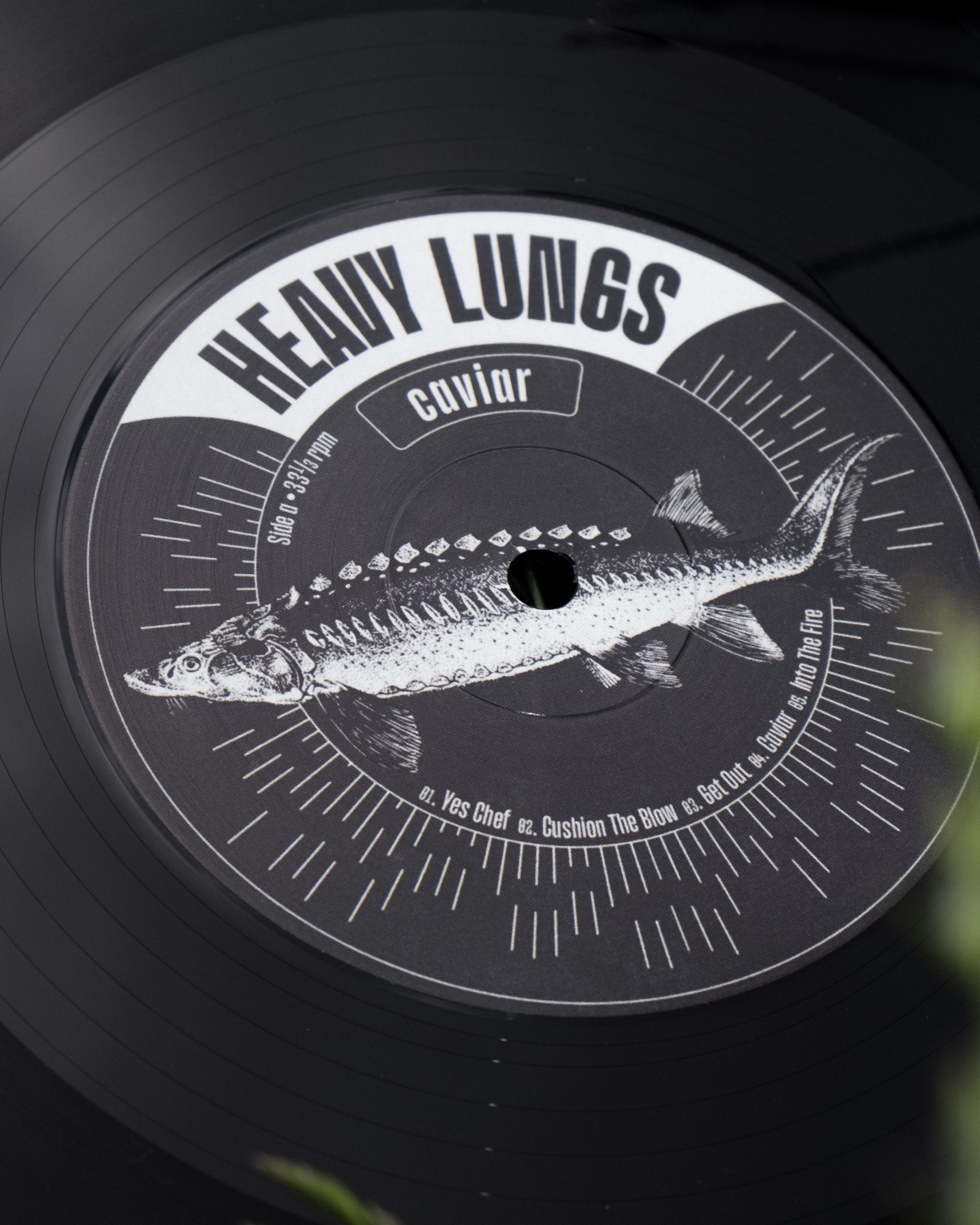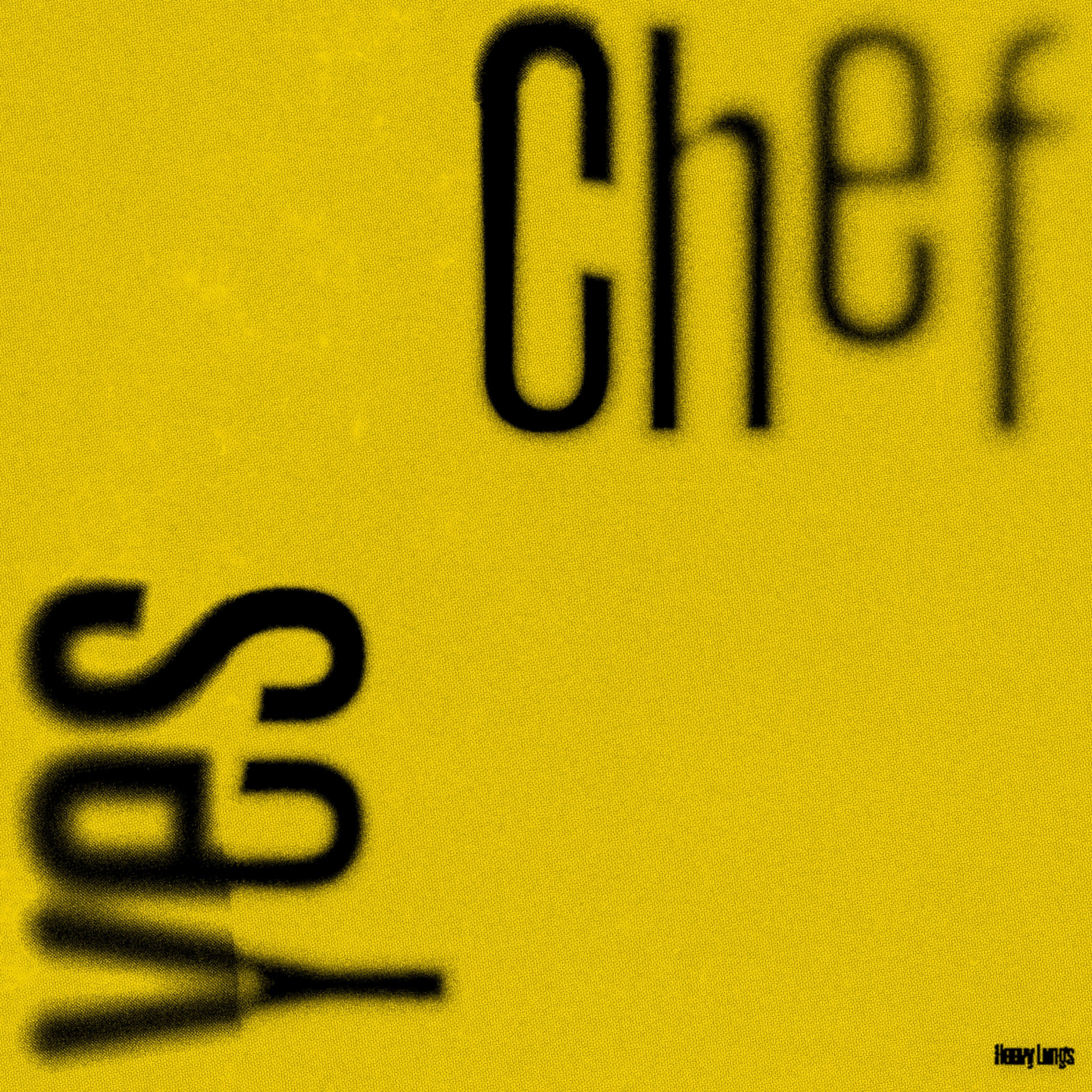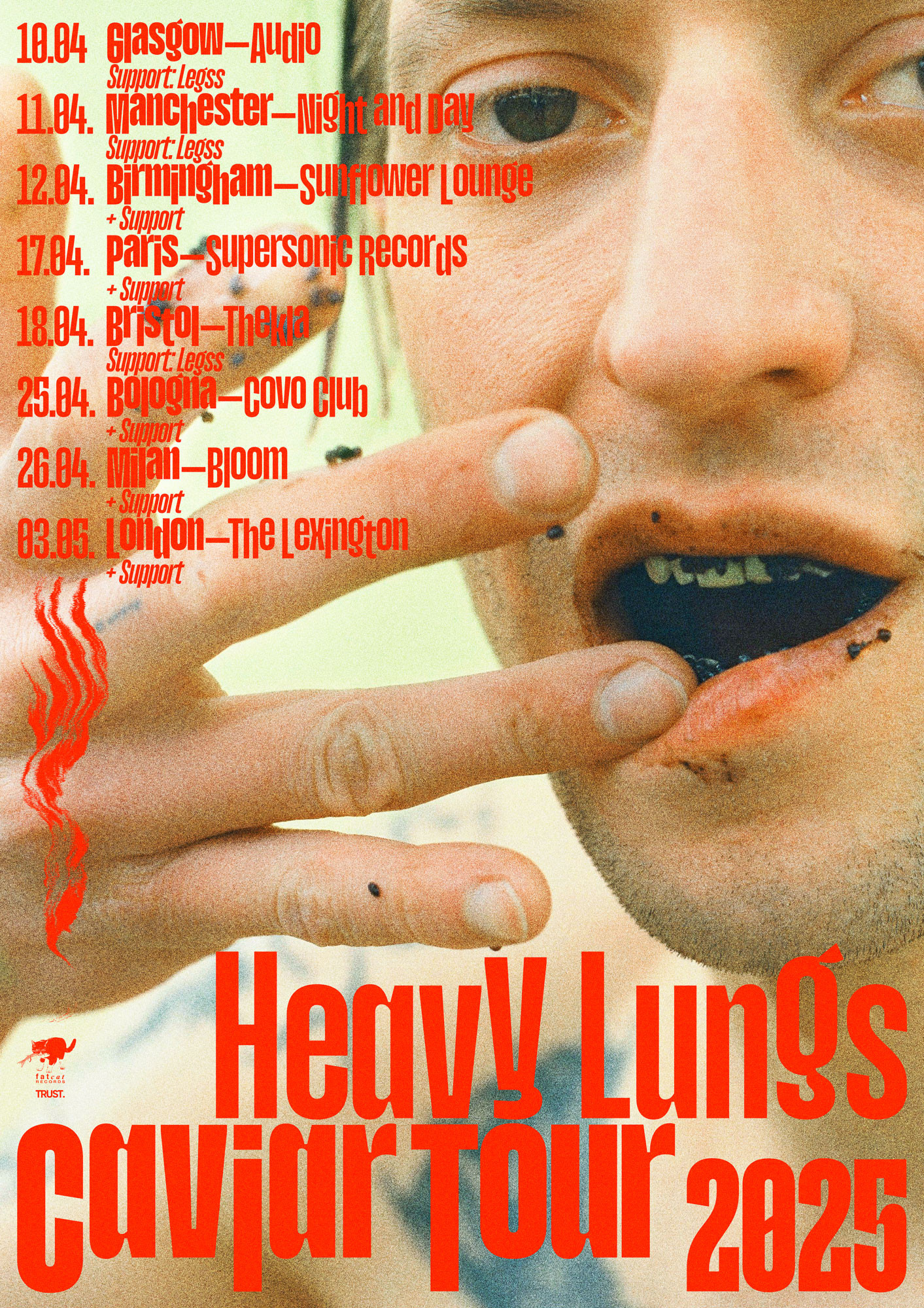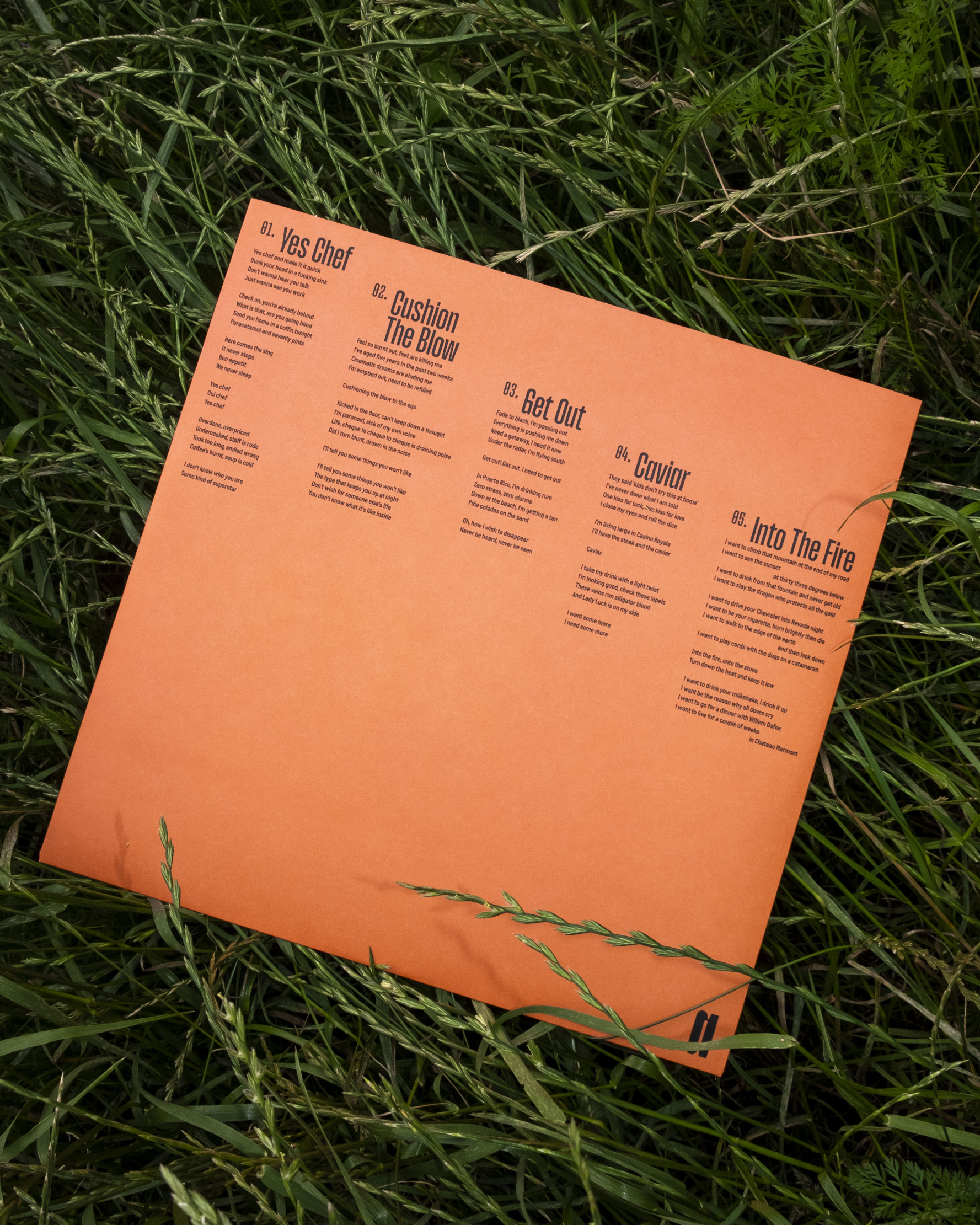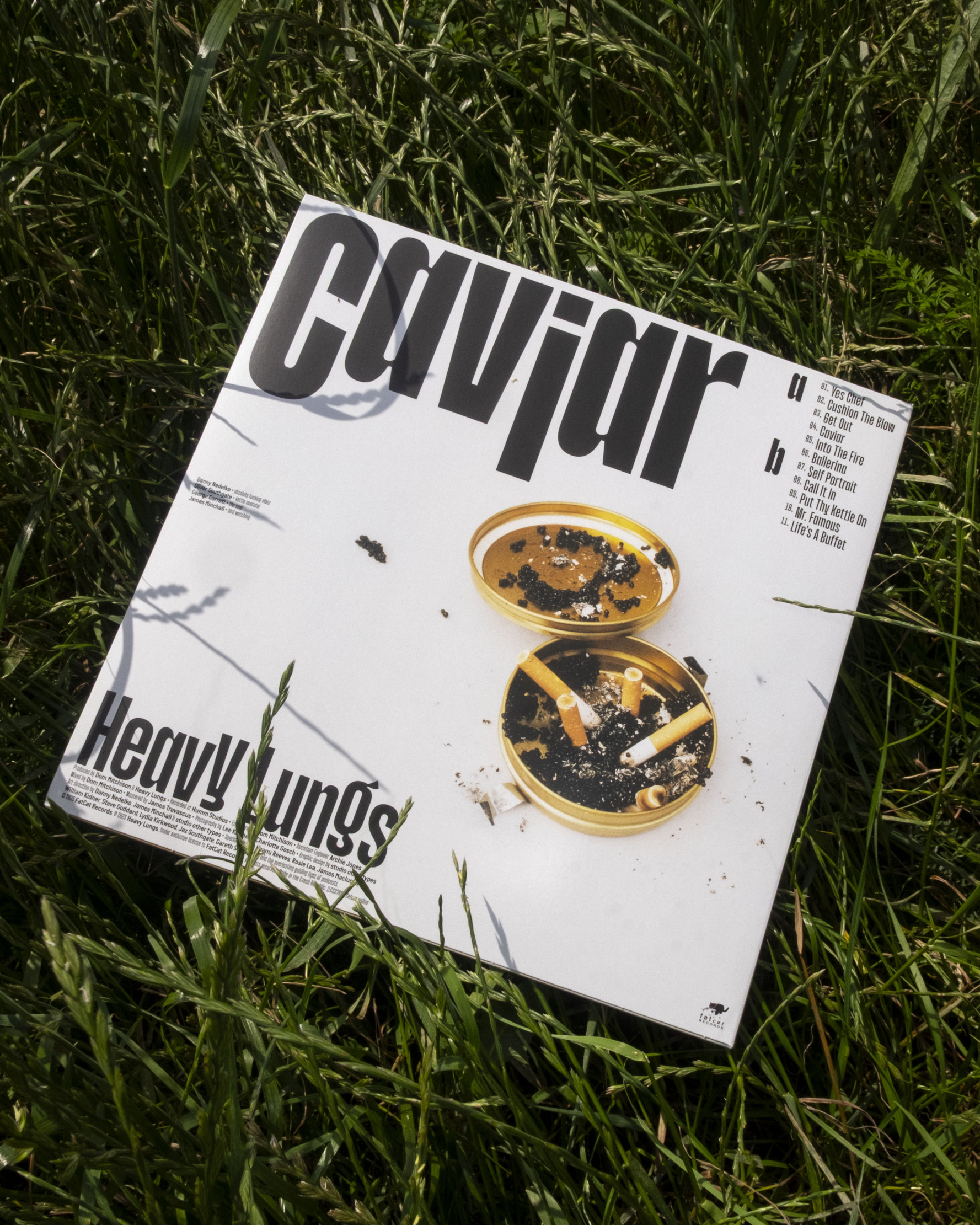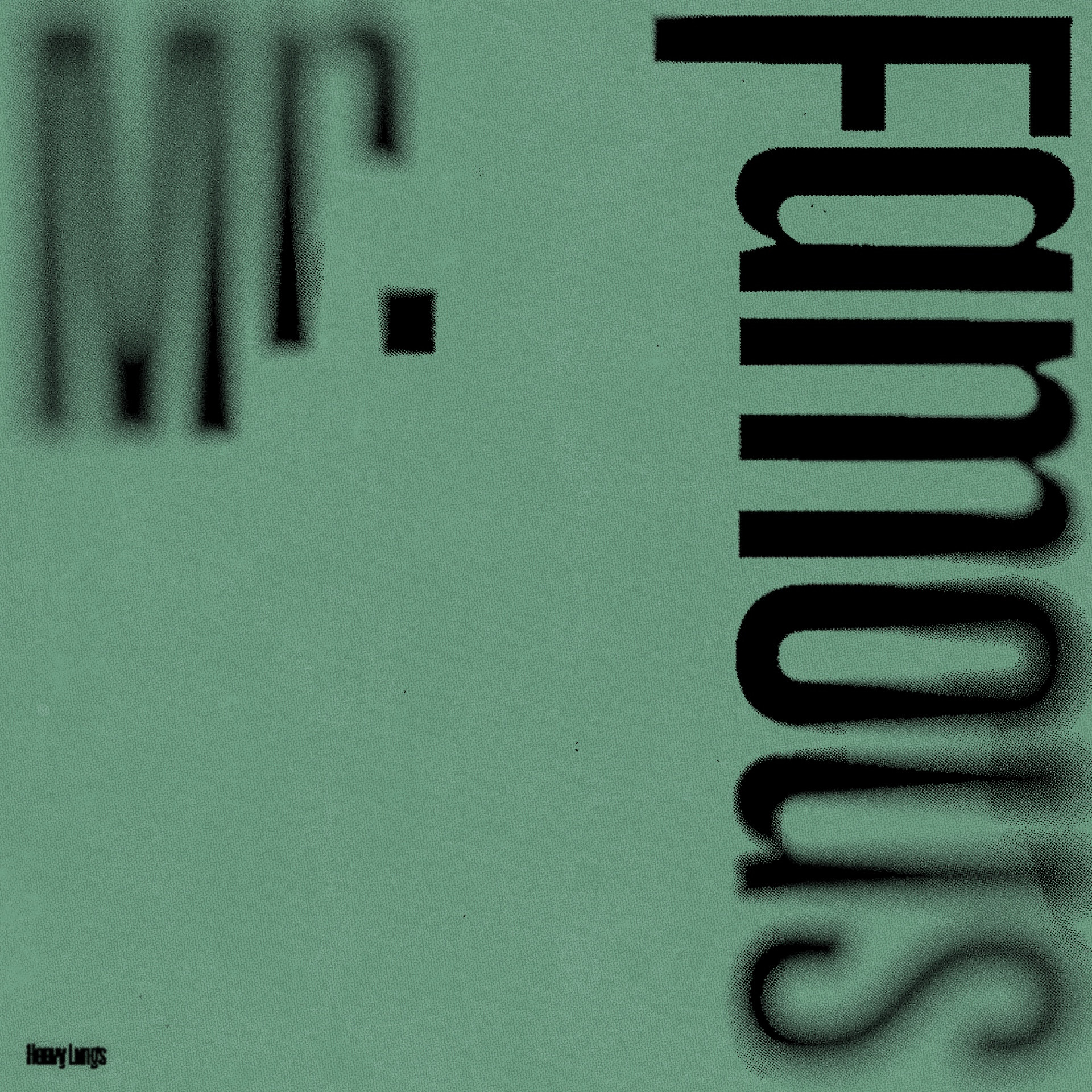
Caviar
Das Albumcover von Caviar der englischen Band Heavy Lungs zeigt im Zentrum den leicht geöffneten Mund von Sänger Danny Nedelko, aus dem Kaviar hervorquillt. Die Bildsprache greift das zentrale Thema des Albums auf: Überfluss, Exzess und ein subversives Punk-Ethos.
Die Rückseite des Albums ist blockig und markant gestaltet. Im Zentrum steht eine leere Kaviardose, die als Aschenbecher dient.
Der Innensleeve überrascht mit einem intensiven Orangeton und ist mit den Songtexten bedruckt. Die Labels der LP erinnern in ihrer Gestaltung an klassische Kaviardosen und spielen bewusst mit deren luxuriöser Anmutung, die durch den düsteren Schwarz-Weiß-Druck gebrochen wird.
Insgesamt vermittelt das Artwork eine rohe, ungeschönte Energie – verstörend, provokativ und passend zur intensiven, rotzigen Klangästhetik des Albums.
Neben dem Albumcover wurden ebenfalls vier Singlecover sowie Tourplakate und Merch in Form von T-Shirts gestaltet.
Schrift: Upton von Halbfett & Italian Plate No2 von Playtype